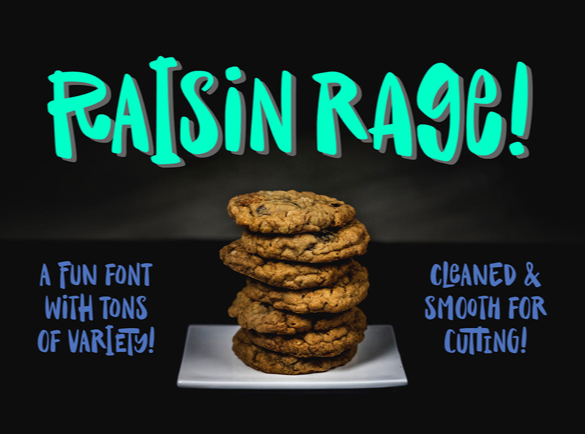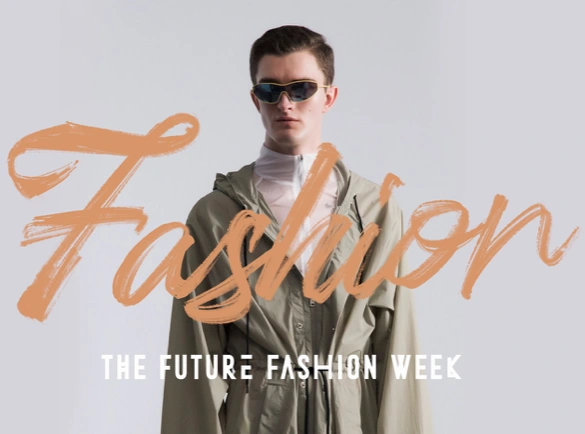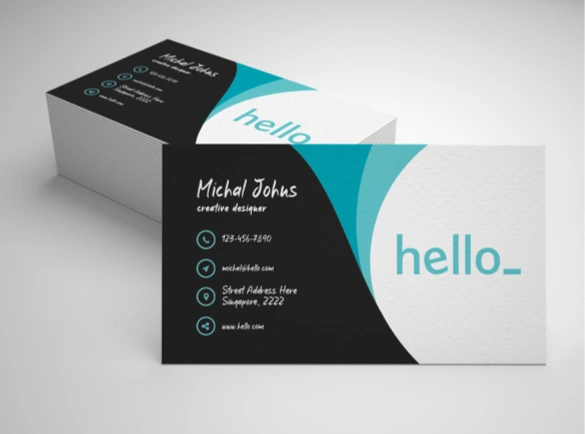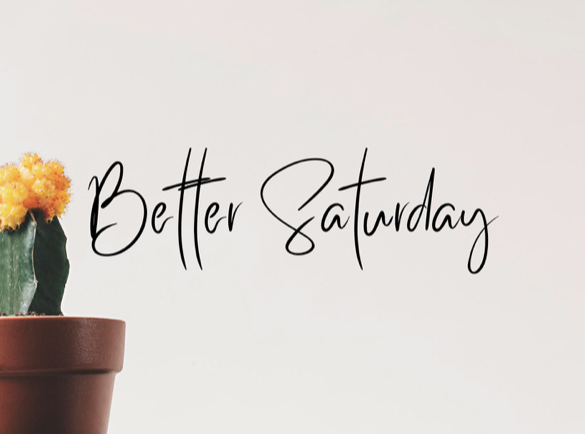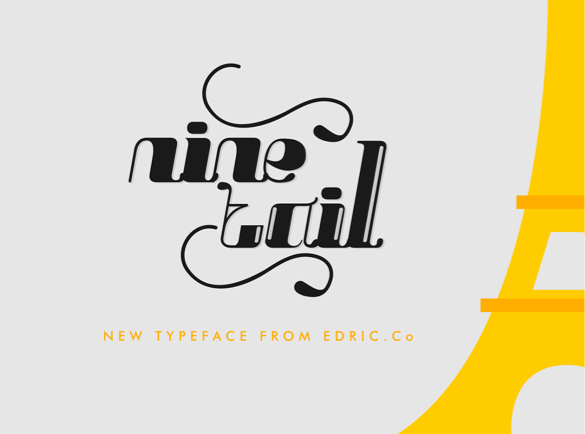
Je Hebt Vast nog Nooit van Deze Coole Fonts Gehoord
Een creatief font zal je merk en en promotiemiddelen er zeker uit laten springen. Vind de inspiratie die je nodig hebt in deze blog!
Wie wordt er nu niet blij van een mooi font? Elizabeth Carey Smith, een ervaren typograaf, zei eens dat typografie gelijk staat aan branding. Wij zijn het daar mee eens. Kiezen voor een font is ontzettend belangrijk voor je merk. Die keuze kan nog wel eens moeilijk zijn met zoveel verschillende keuzes. Bij Drukzo houden we ervan om buiten de gebaande paden te treden, daarom hebben we wat bijzondere fonts geselecteerd die je vast nog niet kende. Let’s go!
Laat een Stempel Achter
Dit font heet 'Marker Mark', en met een goede reden. Het laat de indruk achter dat iemand snel een berichtje voor je heeft achtergelaten. Zou je ook zo graag het handschrift van die persoon willen? Wij zagen gelijk een mooi visitekaartje voor ons met dit font. De stijl zorgt voor een zeer persoonlijke feel, die elk persoon die hem ontvangt het gevoel geeft speciaal te zijn.
Voor de Foodies
We hadden nooit durven dromen dat eten en fonts zo veel gemeen hadden. En dat terwijl er zoveel fonts hun naam danken aan eten. Neem bijvoorbeeld 'Raisin Rage', wat vrij vertaald 'rozijnen razernij' betekent. Dit is een ontzettende vreemde font en wij vinden hem schitterend. De ronde en imperfecte letters doen ons denken aan rozijnenkoekje. Stel je voor hoe goed dit font eruit zou zijn op een flyer. Zo'n uniek ontwerp zal mensen zeker meerdere keren laten kijken.
Er is niets lekkerder bij je koekje dan een goede 'Milkshake'. Dit font is de perfecte combinatie van eenvoudig en pakkend. Het is een kalligrafie font met mooie lijnen die vloeien van letter naar letter. 'Milkshake' is een erg universeel font dat kan worden gebruikt voor veel verschillende doeleinden. Vooral de leesbaarheid is erg fijn.
De Enige Echte
We willen ons allemaal speciaal voelen. We hebben een uniek font, die dat gevoel van exclusiviteit goed over kan brengen. 'Nine Tail' is een speciale combinatie van dikke en dunne lijnen die samen voor een unieke look zorgen. Zet het op een stoepbord voor je winkel en je zult zeker weten de aandacht trekken.
Netjes en Persoonlijk
Ga jij voor klasse? Dan is "Better Saturday" perfect voor jou. Het is de ideale combinatie van typografie met klasse, terwijl het tegelijkertijd een persoonlijke handgeschreven touch heeft. Het is zo'n font die je gebruikt voor een speciale gelegenheid. Het zou er bijvoorbeeld schitterend uitzien op trouwkaarten. Als je een wedding planner bent kun je het zelfs gebruiken voor je logo.
Kunstzinnige Vibes
Geverfde en geborstelde letters. Stereohead is een font met een met de hand geverfde en natte look. Wij vinden hem prachtig. Het font voegt een dimensie toe met schaduw en letterverbindingen. Gepaard met gedurfde en contrasterende fonts wordt het erg modern en pakkend.
We hopen dat je nu genoeg inspiratie hebt gevonden voor een origineel en mooi font voor jouw eigen ontwerp.